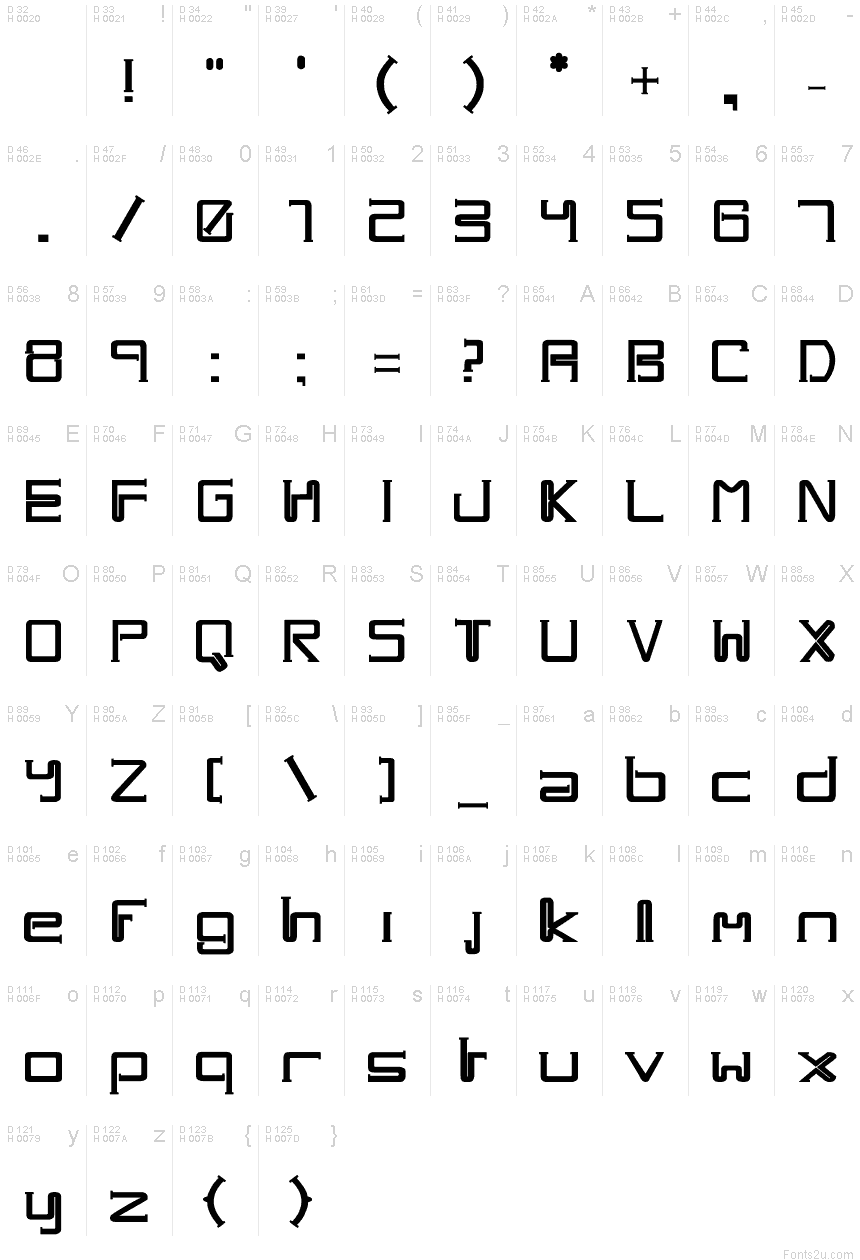
One Way to darmowy krój pisma typu techno display, zbudowany z szerokich, kanciastych pociągnięć, miękko zaokrąglonych rogów i niskiej, wydłużonej sylwetki. Jego kompaktowe formy mają elektroniczny, autorski profil.
Interfejs gry to jego najbardziej przekonujące środowisko, w którym kanciasta geometria może przypominać napisy wtopione w panel sterowania. Te same industrialne kształty pasują do plakatów science-fiction, opraw graficznych muzyki elektronicznej oraz brandingu technologicznego. Jego bezpośrednia, futurystyczna stylistyka jest skierowana do odbiorców gier, klubów i produktów cyfrowych, którzy preferują czystą grafikę przemysłową.